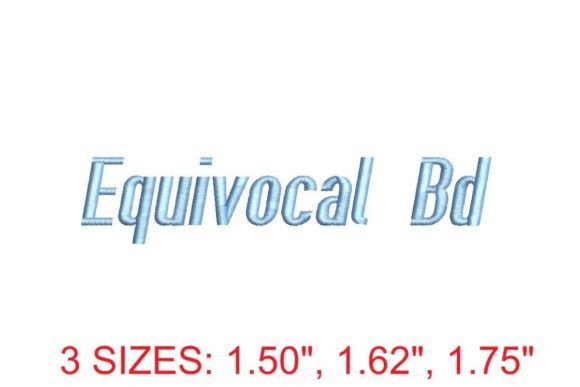
Equivocal BD Embroidery Font
Trouver les bons éléments de conception peut être un défi, mais Equivocal BD Embroidery Font propose une collection exceptionnelle qui rehausse instantanément votre travail.